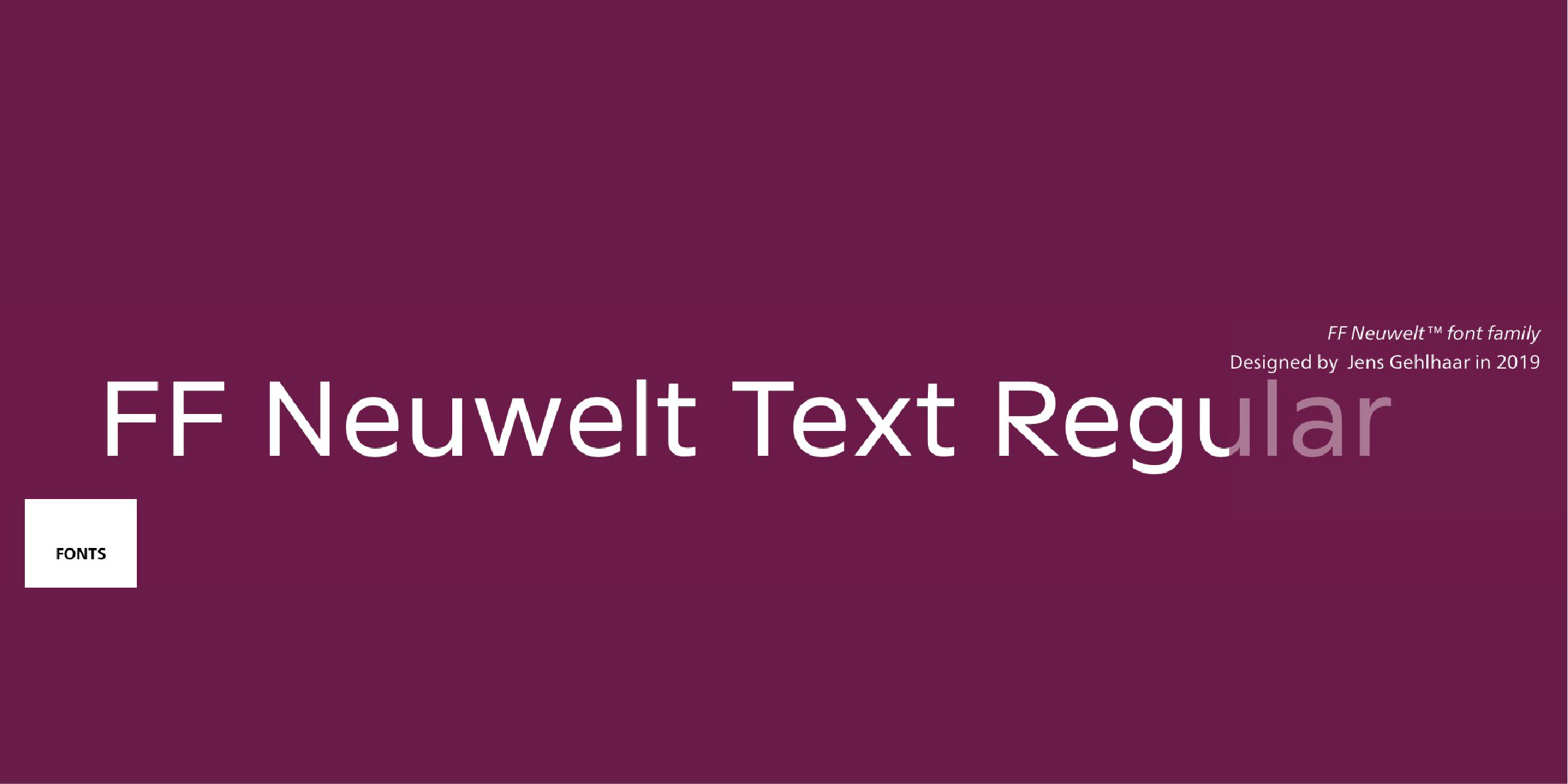
FF Neuwelt™
字体品牌: FontFont(Monotype) 设计师:Gehlhaar,Jens 字体分类:无衬线体 字体属性:外文 字符集:Unicode 发布时间: 2019
此款字体是开放的,有高度易读性。简单的几何形状带来了极高的清晰度, FF Neuwelt 的8个字重与大范围的扩展字符集,使其很少在设计过程中受限。
在坚实的几何无衬线基础上, Gehl haar 绘制了大量的交替字符,注入了 FF Neu welt 的柔和,并最终设计出具有易读性和人文特征的形状和比例。只需轻点鼠标,就可以选择不同的草书斜体形式和圆形或方形标点符号。
FF Neu welt 为大于 16 点的尺寸设置间距,使文本有更多的空间,字母间距也设置了完美的尺寸。此外,五个关键的小写字符被绘制成更清晰的形状,使 FF Neuwelt 适应各种文本尺寸。